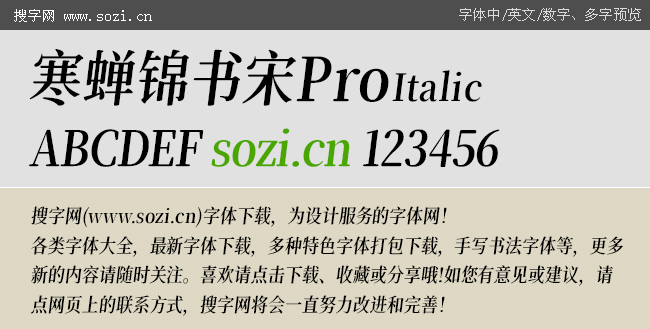
寒蟬錦書宋Pro_Italic
搜字網(wǎng)給大家提供一款寒蟬錦書宋Pro_Italic中文字體下載,寒蟬錦書宋是基于思源宋體進(jìn)行修改的一款字體,在思源宋的基礎(chǔ)上添加圓角,變成更加溫潤的宋體,排版細(xì)節(jié)優(yōu)化,重構(gòu)字重比例,使字體粗細(xì)更加均衡,便于閱讀,這款為斜體字體,適用于標(biāo)題設(shè)計(jì)、海報(bào)設(shè)計(jì)、書籍排版以及網(wǎng)頁設(shè)計(jì)等應(yīng)用。